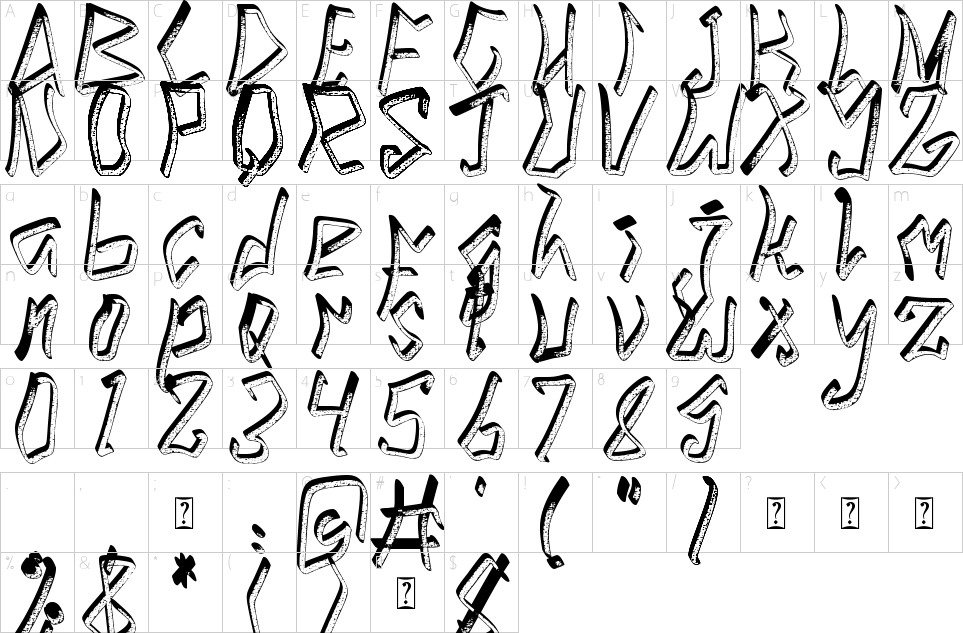
Galaxy Power Font
Descubra a elegância sofisticada da Galaxy Power Font para suas próximas criações de design. Desenvolvida por Yoga Letter, esta fonte oferece uma combinação única de simplicidade e modernidade que vai se adequar perfeitamente ao seu projeto, seja ele em ambientes Windows ou Mac. Com 818 downloads desde sua disponibilização, a Galaxy Power Font tem provado ser um recurso valioso para designers gráficos de todo o mundo. Seja para textos profissionais ou elementos visuais criativos, esta fonte traz um toque distintivo que enriquece qualquer layout. Experimente agora e dê vida a suas ideias com este poderoso instrumento de design disponível gratuitamente.